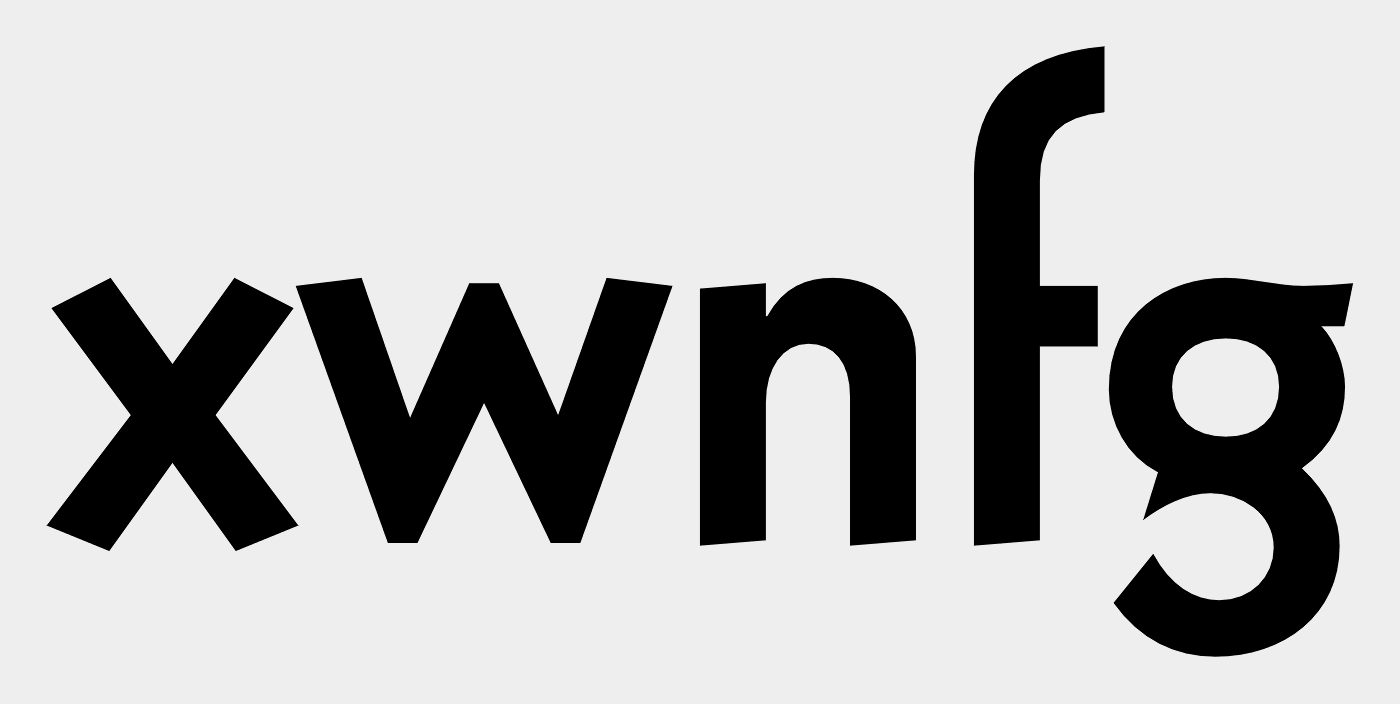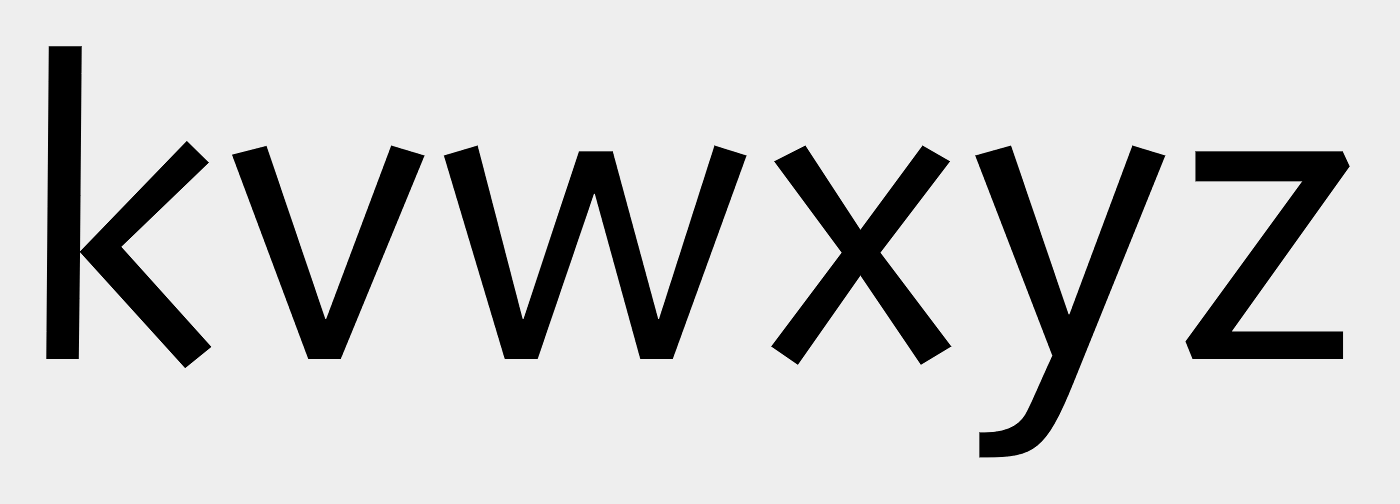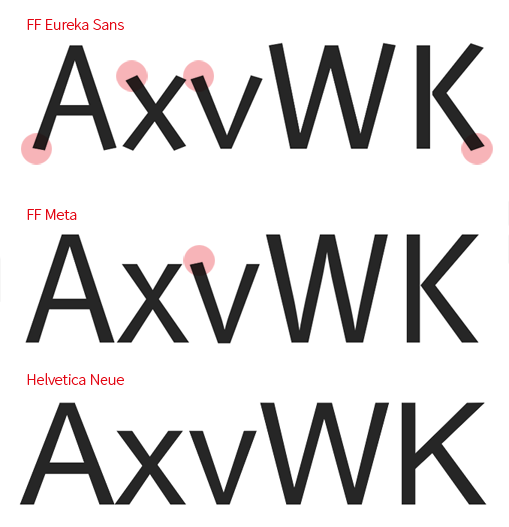
Angewinkelte Strichenden
Ein frohes neues Jahr allerseits. Mir ist in letzter Zeit aufgefallen, dass es überraschend wenige serifenlose Schriftarten gibt, bei denen die Enden der Buchstaben A, V, W, X, Y (und zu einem Teil auch R und K) angewinkelt sind. Zumindest sind diese Schriften deutlich in der Minderheit. Woran liegt das?
In Karen Cheng's "Designing Type" geht sie ganz kurz darauf ein, indem sie eine Abbildung der FF Eureka Sans zeigt; ansonsten konnte ich dazu nicht viel finden. Gibt es dazu bereits eine Diskussion, oder gibt es ganz offensichtliche Nachteile, die bei der Wahl in der Regel immer dazu führen, dass die Enden an die Grundlinien angepasst werden? Oder täuscht der Eindruck, und Winkel sind das Next Big Thing?
Zum besseren Verständnis meiner Frage hier eine kurze Illustration:
Ich denke, dass die durchgehende Linien, die sich ergeben, zu einem besseren Fluss in Lesegrößen führen. Die Eureka springt schon deutlich. Mir fällt das auch bei Rounded-Schriften auf, die ich schwerer zu lesen finde als waagerecht begrenzte.
Na gut, es stimmt, dass durch die rechten Winkel die Linienführung unterbrochen wird und das Ganze etwas springend wirkt. Dann ist das vermutlich eher etwas für Display-Schriften. Allerdings gibt es natürlich auch schöne Beispiele, wie man trotzdem eleganten Fließtext setzen kann. Aus dem Link von R::bert bin ich z.B. auf die Jigsaw gestoßen: https://www.typotheque.com/fonts/jigsaw
Ich bastele seit ein paar Jahren an einer Schrift, bei der ich mich einfach nicht entscheiden kann, wie ich mit diesem Problem umgehen möchte. Mir kommt der Eureka/Jigsaw-Ansatz intuitiver vor; die Buchstaben in einen Kasten zwischen Grundlinie und x-Höhe zu quetschen widerstrebt mir. (Das gilt vor allem für das "x", wo ich gefühlt viermal die natürlichen Enden schneiden muss. Ich sehe natürlich ein, dass das albern ist. Ist einfach ein komisches Bauchgefühl.)
Mir ist noch die Skia und Lithos eingefallen.
Kommt wohl auch darauf an, ob die Schrift eher für Schaugrößen oder  Lesegrößen zugeschnitten bzw. eingesetzt werden soll. Man könnte ja auch über zwei Varianten nachdenken.
Ich persönlich finde auch, dass sie durch die schrägen Strichenden etwas archaischer und lebendiger wirkt, was ja durchaus reizvoll sein kann.
Ist das nicht bei der Kabel (zumindest bei den Versalien) auch so, dass die Strichenden "schräg" sind? Und außerdem verbinde ich das oft auch mit den Covern von Ligne-Claire-Comics …